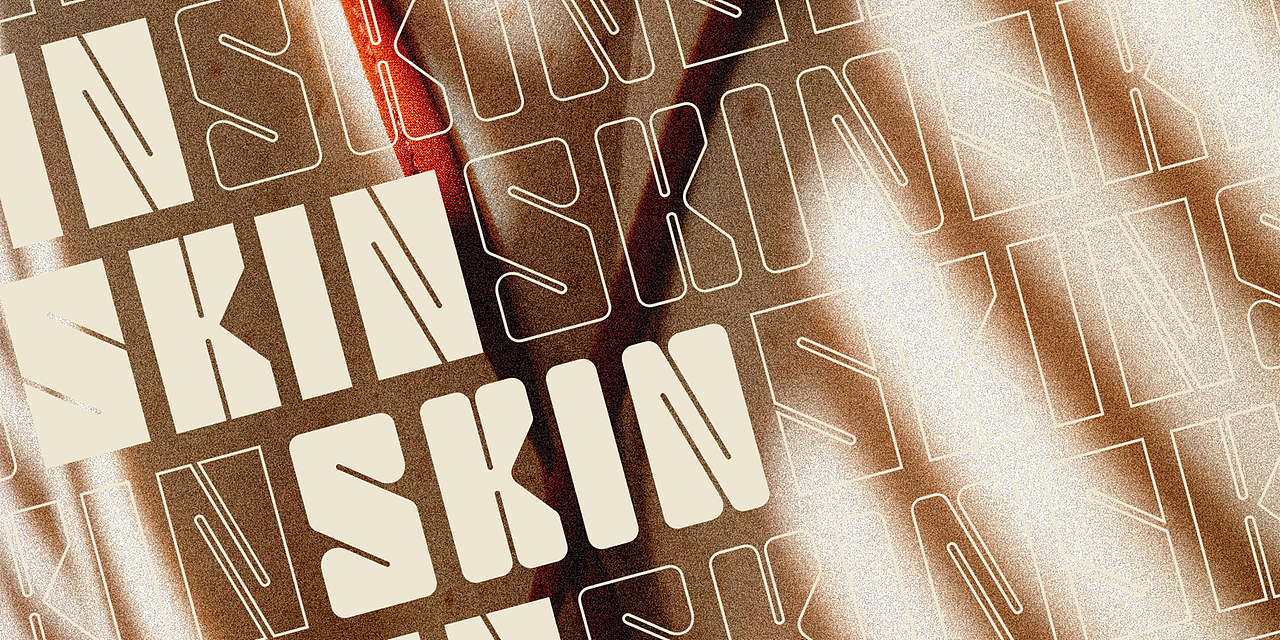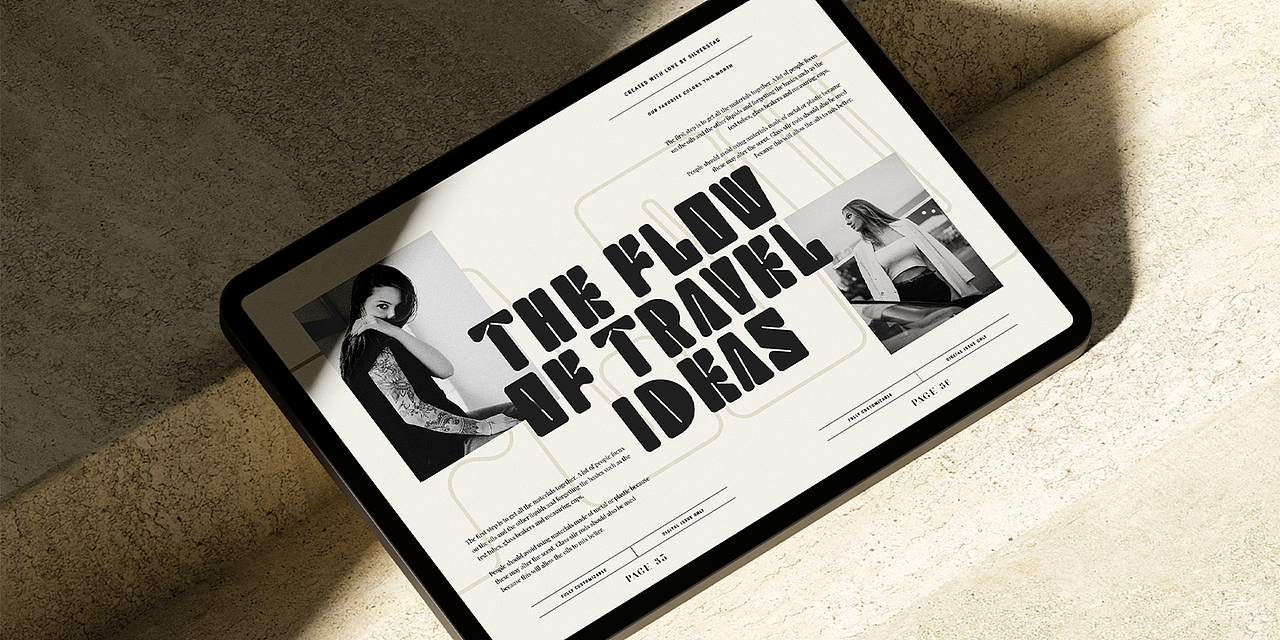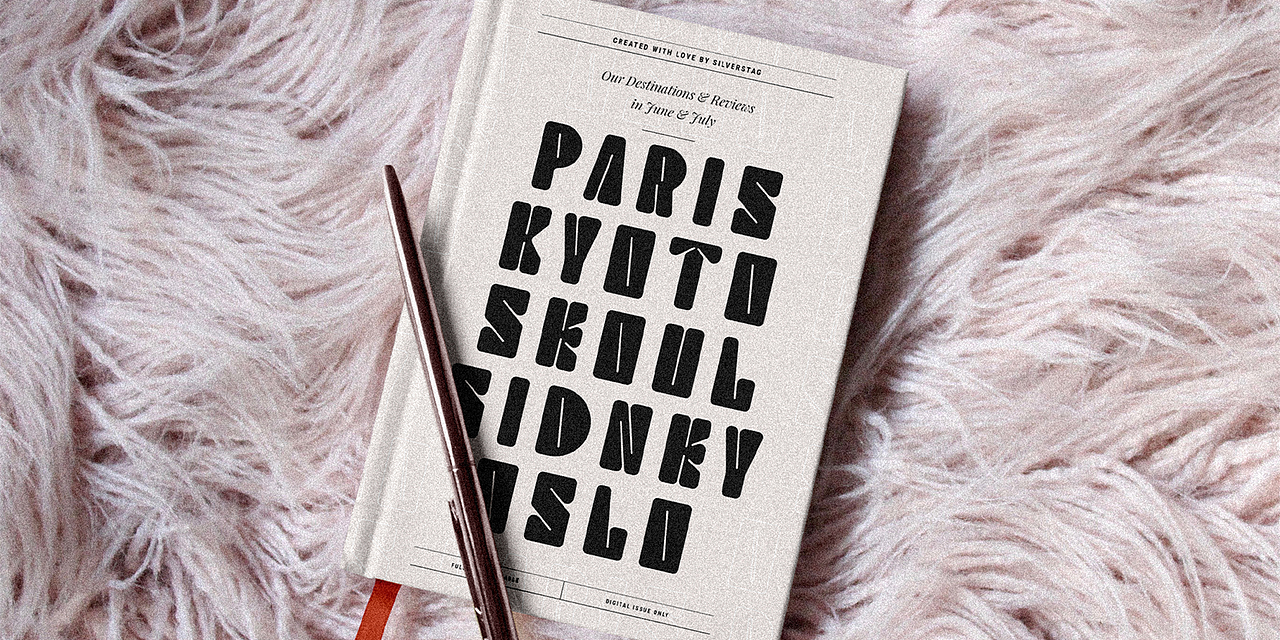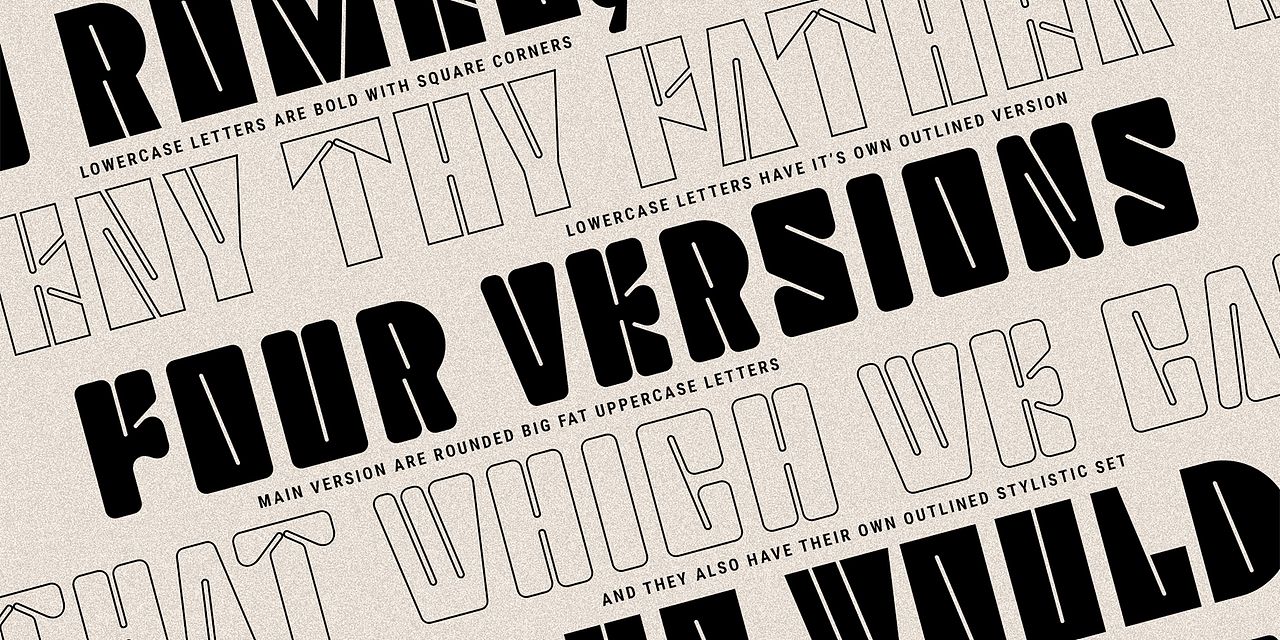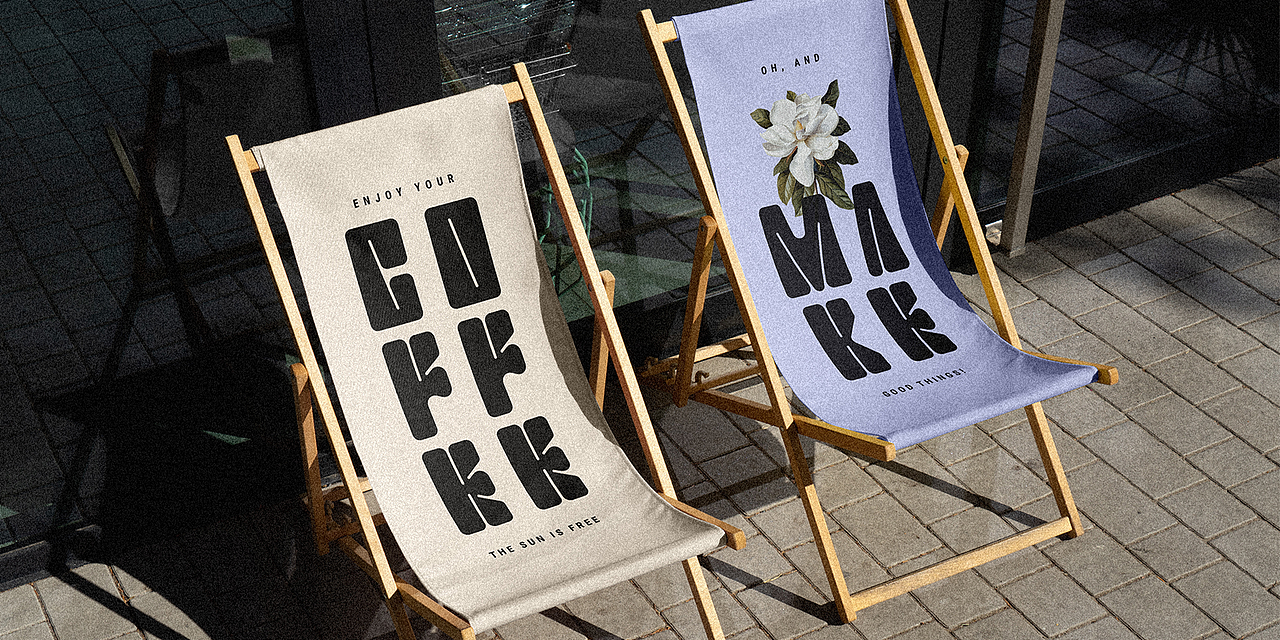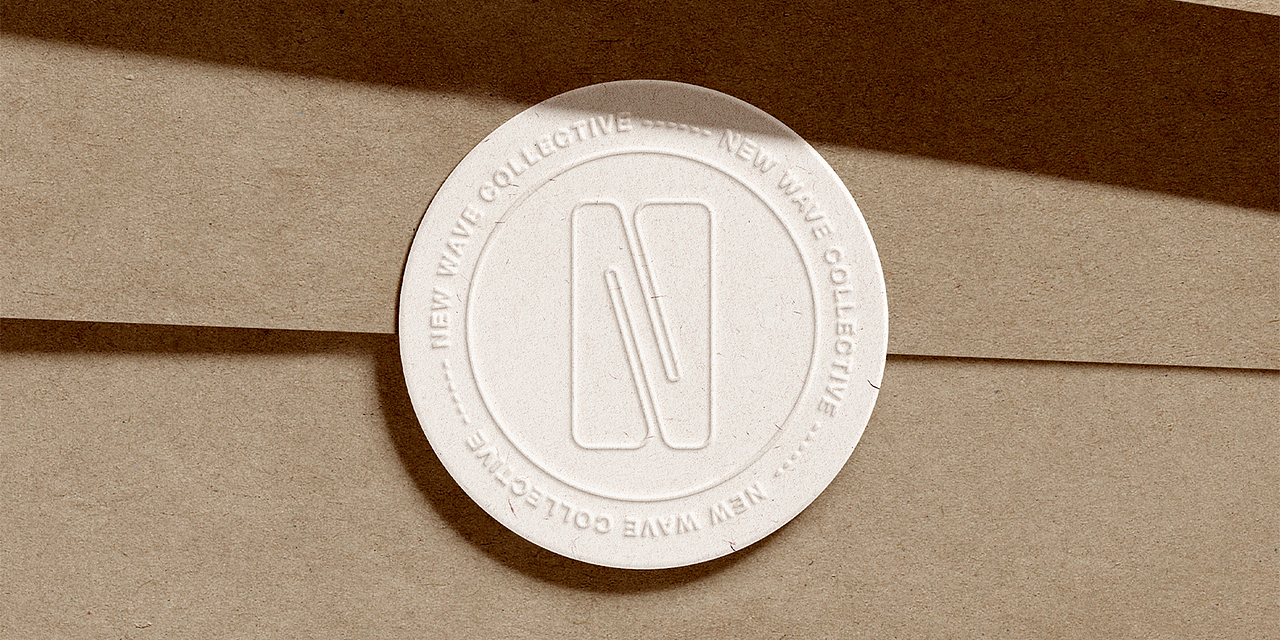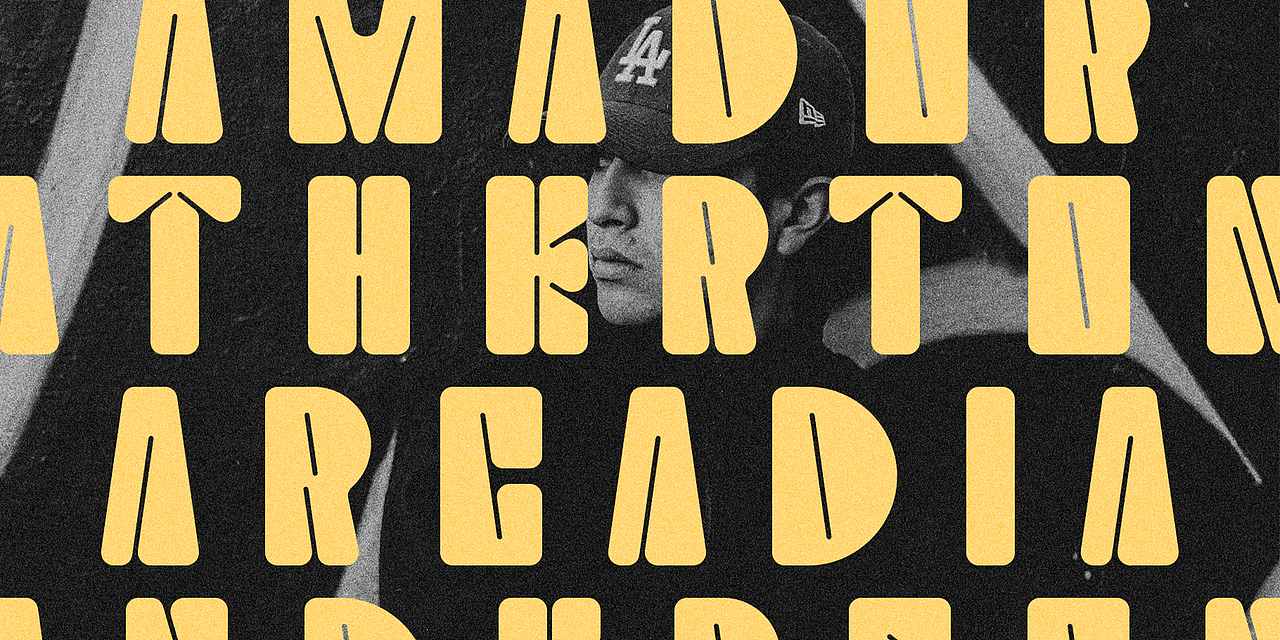
Bolt Display:大写字母也能有温暖轮廓
Bolt Display 是一款大写字体家族,结构颇具巧思,质感敦实但不厚重,并通过圆角细节呈现温暖亲和的氛围。整体来看曲线优美,个性独特。这款字体还提供镂空样式,能够为创意作品增添更多大胆的现代气息。
通过样张也能够感受到,Bolt Display 无论是应用于实体物料,还是数字媒介,都展现出极强的视觉表达力,为创意作品增添温暖的触感,在结构与艺术间取得了平衡。